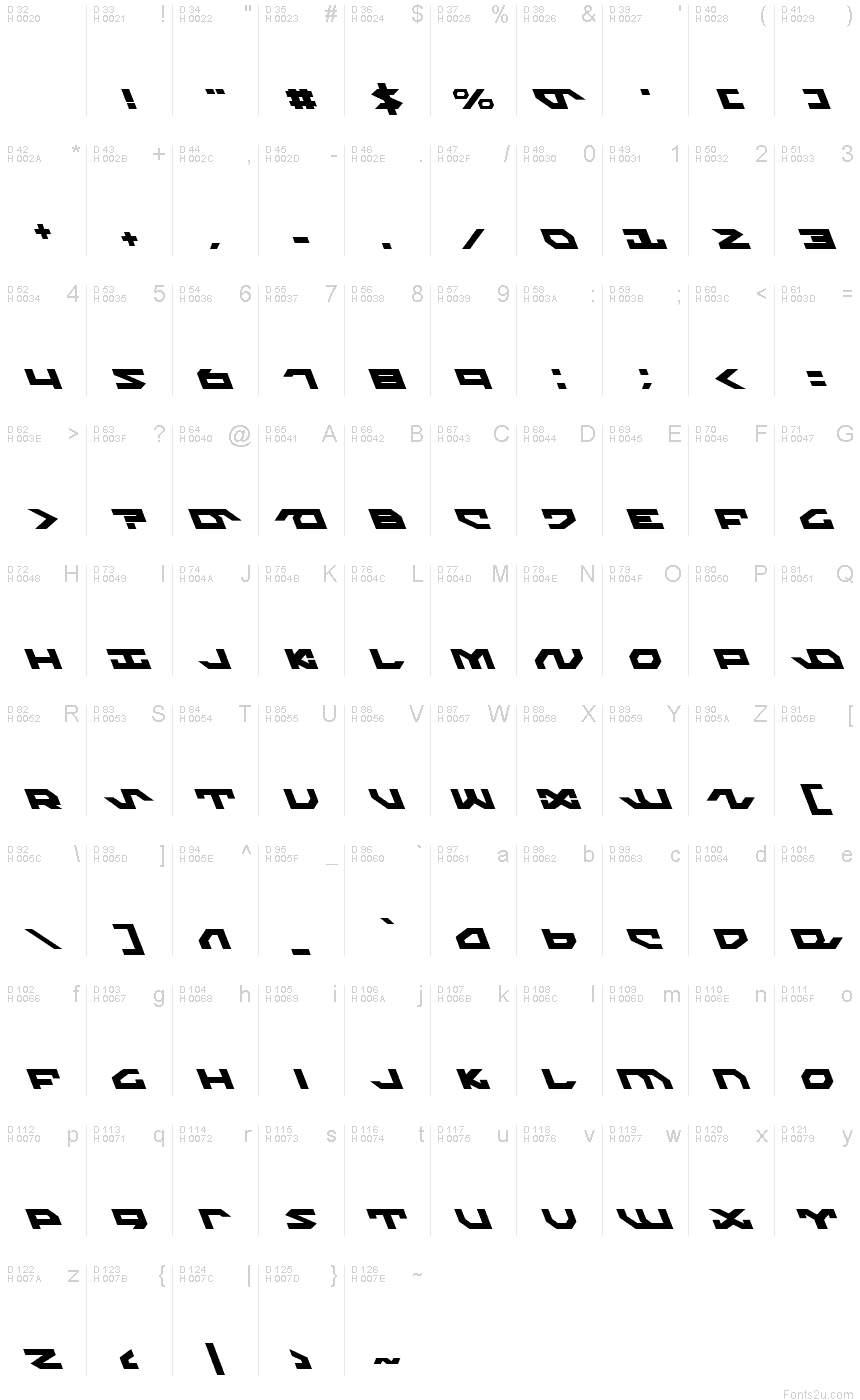
Nightrunner Leftalic, creata da Iconian Fonts nel 2008, è un carattere display gratuito dallo stile techno futuristico, costruito su forme geometriche ampie e dai tagli netti. Le lettere combinano cunei diagonali slanciati con aperture rettangolari strette, creando un ritmo tecnico che richiama le livree delle astronavi e le interfacce dell'era arcade.
Il forte movimento direzionale conferisce ai progetti di branding e ai titoli dei giochi un senso di velocità, mentre la silhouette angolare è perfetta per la grafica esports e le campagne di poster sci-fi. Utilizza questo font gratuito per la segnaletica di eventi motoristici o per il packaging di musica elettronica, quando il lettering deve integrarsi alla perfezione con immagini taglienti e layout dinamici.